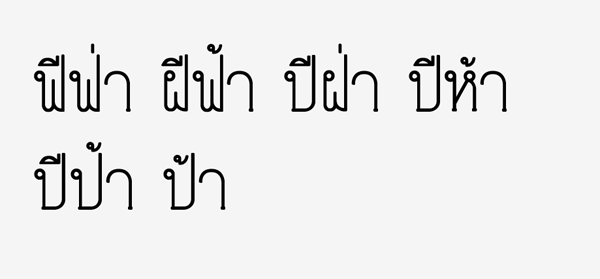
Nithan
นิทาน เป็นหนึ่งในชุดตัวอักษรที่ได้ออกแบบ และส่งในงาน TFace2
คอนเซปต์หลักคือ เป็นฟอนต์ความเรียงที่ดูเรียบร้อย และน่ารัก
เหมาะสำหรับเด็กๆ อย่างเนื้อหาในหนังสือนิทาน หรืองานที่ต้องการให้ดูเด็กๆ
เป็นหนึ่งในฟอนต์ที่ส่งงาน TFace2 ที่ผ่านมาค่ะ (ส่งไป 3 ตัว)
เพิ่งเคยทำครั้งแรก ดำน้ำไล่อ่านกระทู้ในบอร์ดหน้าแรกยันหน้าสุดท้าย(แบบรู้เรื่องบ้างไม่รู้บ้าง)
ตัวนี้จริงๆคือทำเสร็จตั้งแต่ก่อนมีงานสัมมนาแล้ว และหลังจากฟังสัมมนาแล้ว คิดว่าต้องปรับแก้ใหม่หลายๆอย่าง (ซึ่งก็ยังไม่ได้ทำ  :08:)
(แถมทิ้งไว้หลายวัน วันนี้มาดูอีกทีเคิร์นนิ่งช่องไฟบูดๆเบี้ยวๆมากเลย  :08:)
ชื่อฟอนต์ Nithan
คอนเซปต์หลักคืออยากได้ฟอนต์ตัวเนื้อที่เรียบร้อย และดูน่ารักให้ความรู้สึกแบบเด็กๆ
ปรับช่องไฟห่างอีกนิดงามหยดเลยนะคะฟอนต์นี้ :25:
:25: อึ๊ย น่าเอามาทำตัวเนื้อในนิทานจริงๆ ด้วย
ลองปรับพวกช่องไฟดูนะครับ มันยังเบียดๆ กันอยู่ (ดูตัวอย่างคำว่า มิติ นะ)
แล้วก็ความแคบ - กว้าง ของตัวอักษรน่ะครับ อย่าง ง งู รู้สึกจะผอมไปนิดนึง
เวลาปรับช่องไฟของสระไอ ต่างๆ เราสามารถปรับให้มันกว้างได้กว่านี้นะครับ เพื่อที่จะเผื่อเวลามันไปชนวรรณยุกต์บนด้วย
ประมาณนี้
แก้ช่องไฟใหม่ค่ะ ยังกะจังหวะไม่ค่อยถูกนัก ใช้วิธีดูตัวคอร์เดียเป็นต้นแบบ แล้วมากะๆเอา
ยังไม่ได้ปรับเคิร์นนิ่ง (จริงๆคือปรับไปได้ครึ่งหนึ่งแล้ว แล้วลืมเซฟ   :07:)
ลองซ้อนกะอันเก่าดู ต่างกันอย่างเห็นได้ชัด
ยังไม่ได้เช็คตัวอังกฤษ เพิ่งเห็นปัญหาระหว่าง Y กับ o ตอนโพส
อันนี้เป็นปัญหาที่พบค่ะ
เวลาพิมพ์ตัวหางยาว+สระประเภทอิ อี แล้วต่อด้วยตัวหางยาว+พวกไม้เอก โท
ไม้เอก ไม้โทจะลอย ไม่รู้ว่าแก้ยังไง เป็นแค่กลุ่มนี้  :08:
มีปัญหากับฟีฟ่า ติดต่อบังยี 55+
ปล. เพิ่งสังเกต ไอ้พวก ฟีฟ่า ปีป้า เหมือนกันนี่ ไม่แปลก
มีลอง ปีห้า เหมือนกันด้วย 55+
แก้ช่องไฟแล้วดูดีมากเลย :25:
ดูดีขึ้นมากจริงๆ ด้วยครับ :25:
ทีนี้ดูพวกพื้นที่ว่างที่มันยังเป็นปื้นๆ อีกนิดนะครับ (เช่นคำว่า แต่ ข้างบนนู่น)
อาจจะต้องจับเกลี่ยๆ กันให้มันโปร่งเป็นระบบเดียวกัน
โอ๊ย ชอบ น่ารักน่าใคร่ :25:
หรี่ตาดูเลยค่ะ สะดุดตรงไหนแก้ตรงนั้น :25:
ตัวภาษาอังกฤษ คำว่า head มันติดกันไปนิดนึงไหมอ่ะครับ :25:
ชอบตัวภาษาอังกฤษแหละ  :27: